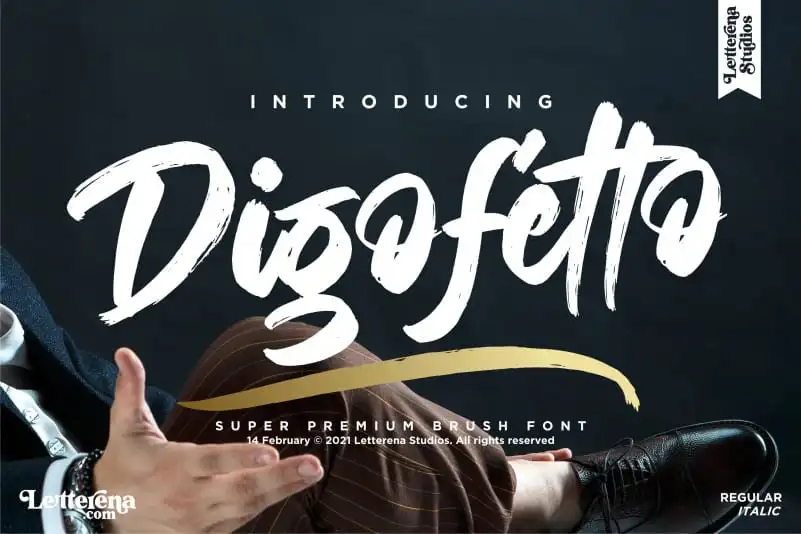
Digofetto Brush Font – Download Grátis
A “Digofetto Brush Font” é uma elegante seleção entre as fuentes brush do mercado. Desenvolvida pelo Designer Letterenastudios, esta fonte premium oferece um estilo forte e expressivo que se encaixa perfeitamente em projetos variados. Com sua tipografia vigorosa e contornada, a Digofetto Brush atende perfeitamente para criações como logos, produtos de embalagem, t-shirts, revistas ou editoriais de livros, cartões de visita, etiquetas de produto e até mesmo materiais de eventos especiais. A qualidade robusta da fonte faz dela uma escolha ideal não apenas para projetos de design gráfico tradicionais, mas também para artigos pessoais como cartões de aniversário ou impressões digitais. A Digofetto Brush é a escolha perfeita se você busca um toque brilhante e único para seus trabalhos criativos, seja em uma t-shirt com sua frase preferida ou em uma embalagem sofisticada do seu produto novo.